W kreatorze Najszybsza masz do wyboru ponad 100 najpopularniejszych czcionek Google Fonts. Większość z nich to tzw. CZCIONKI ZMIENNE (VARIABLE FONTS).
Czcionki zmienne to nowoczesna technologia typograficzna, która umożliwia dynamiczną zmianę różnych parametrów czcionki, takich jak grubość, szerokość czy nachylenie. W kreatorze udostępniamy zmianę grubości czcionki gdyż jest ona wspierana przez wszystkie czcionki zmienne.
W każdym elemencie tekstowym możesz pogrubić czcionkę lub nadać jej lekkości. Dzięki takiemu rozwiązaniu możesz podkreślić istotne elementy bez konieczności zmiany kroju czcionki. Pozwala to zachować spójność stylistyczną na stronie.
Dla większości czcionek zmiennych możesz wybrać grubości:
Przykład czcionki Manrope w różnych grubościach:
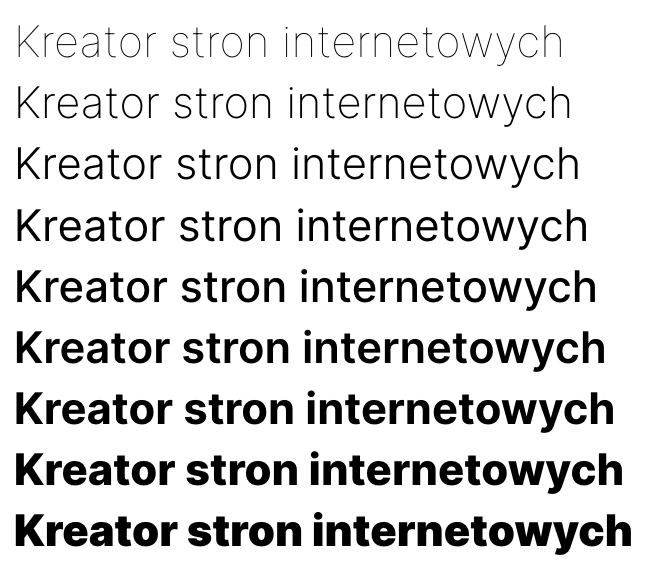
Nie wszystkie czcionki Google Fonts są czcionkami zmiennymi oraz nie wszystkie czcionki zmienne mają wszystkie dostępne grubości. Kolekcja jest jednak sukcesywnie rozszerzana przez twórców Google Fonts. Jeżeli ustawisz grubość, której wybrana czcionka nie posiada to przeglądarka zastosuje najbliższą dostępną.